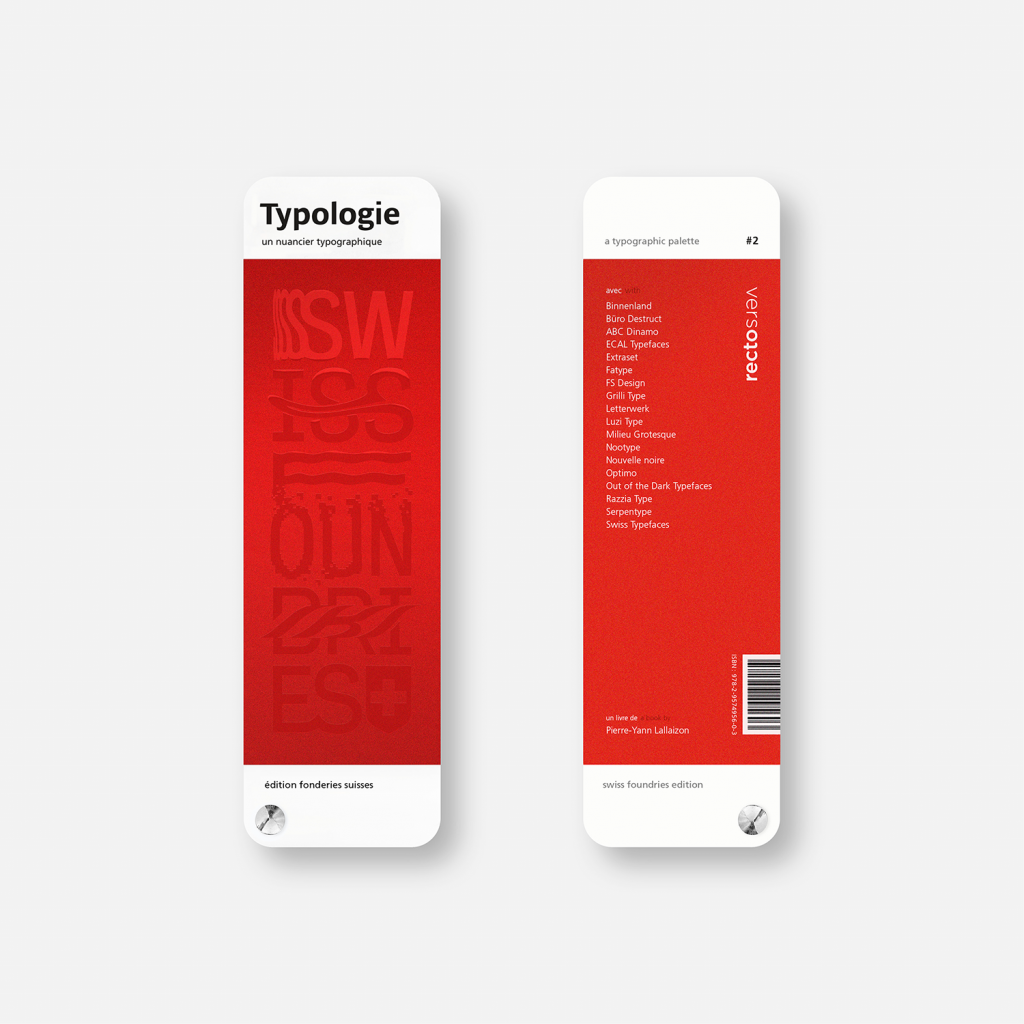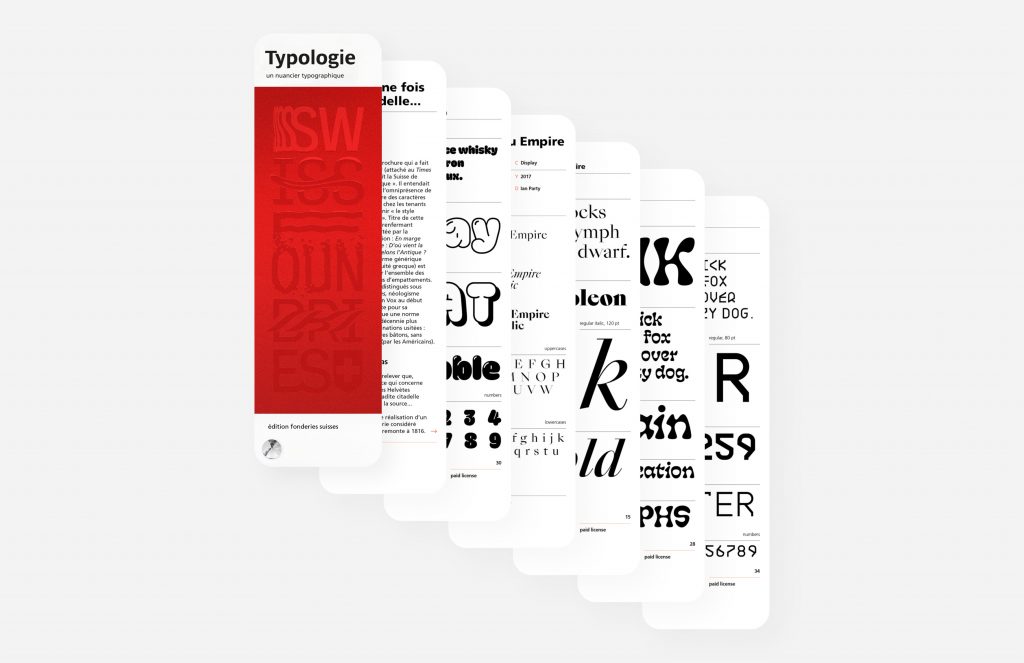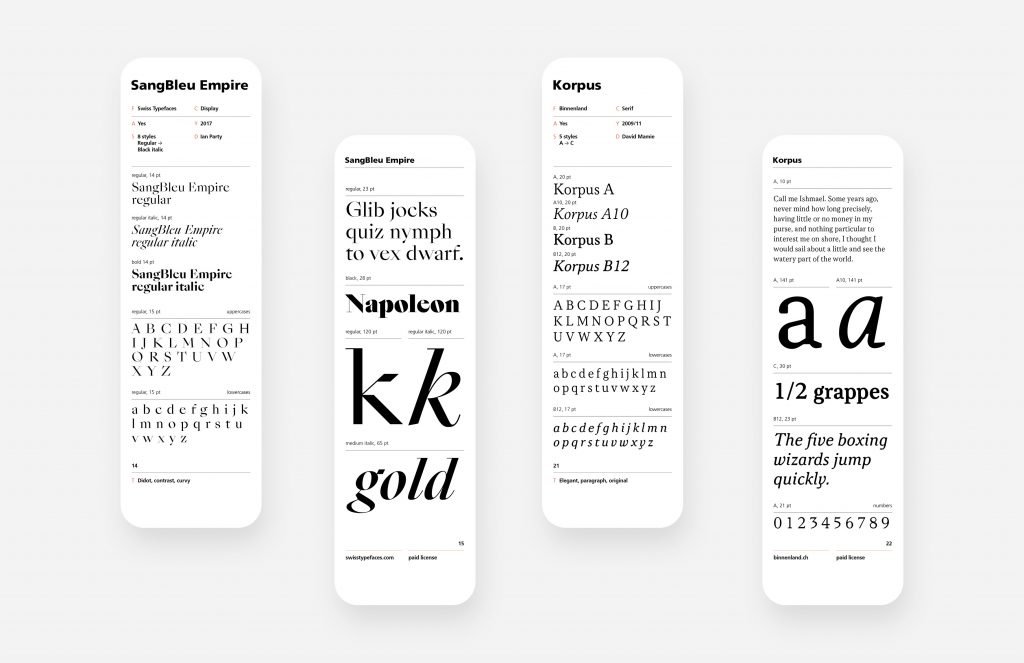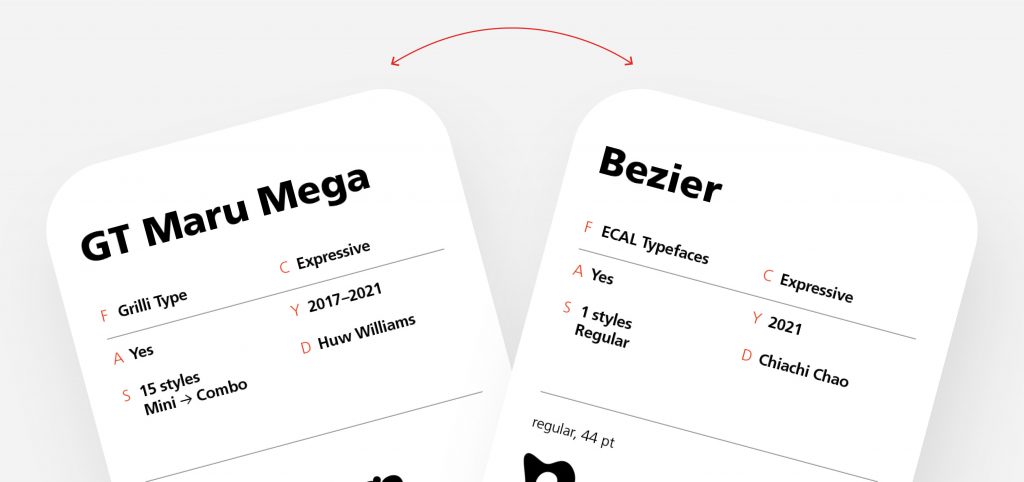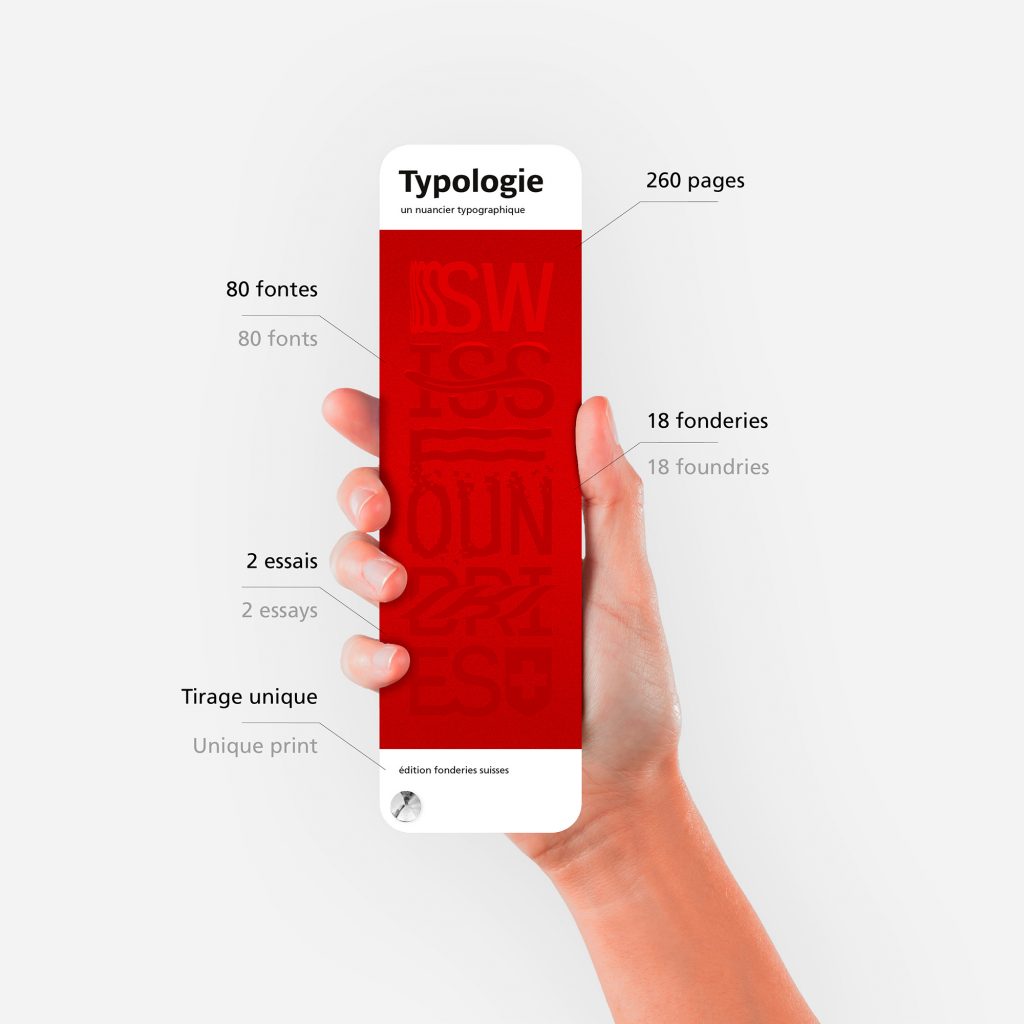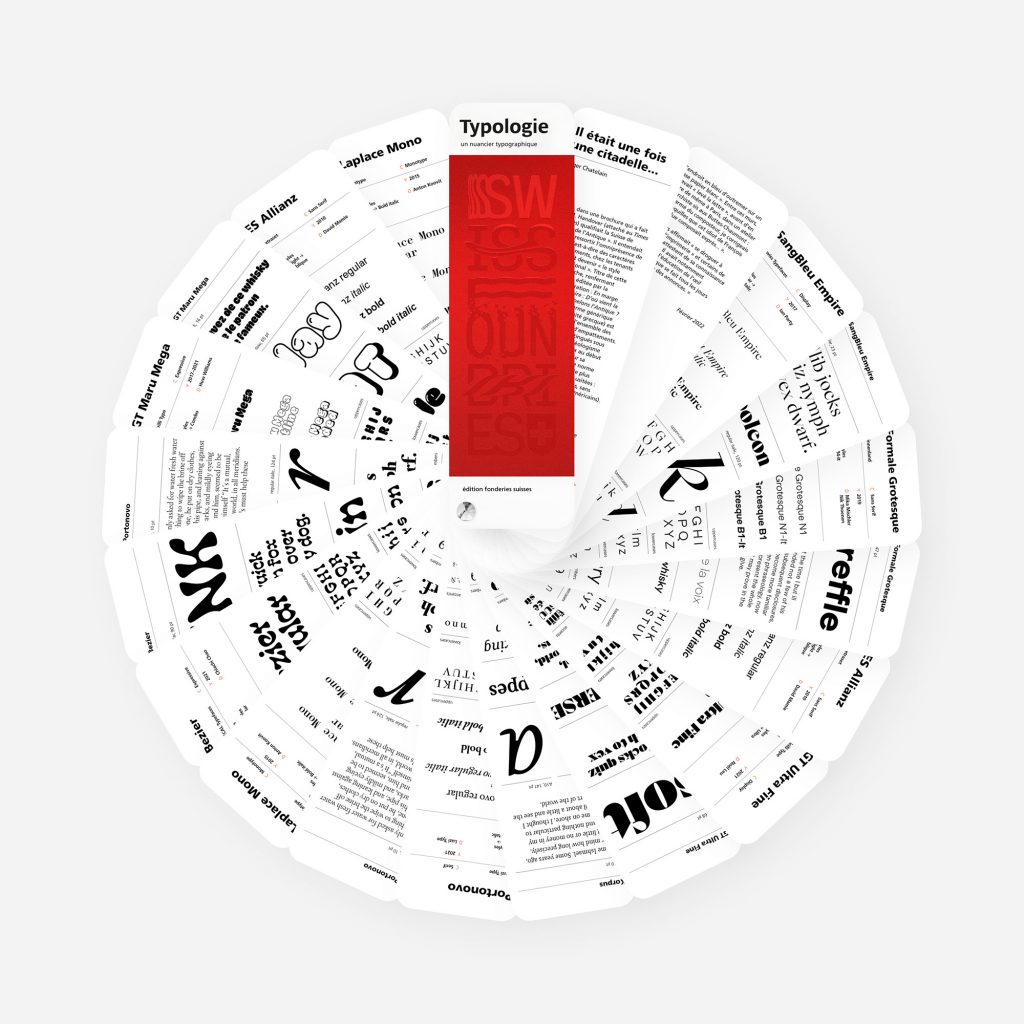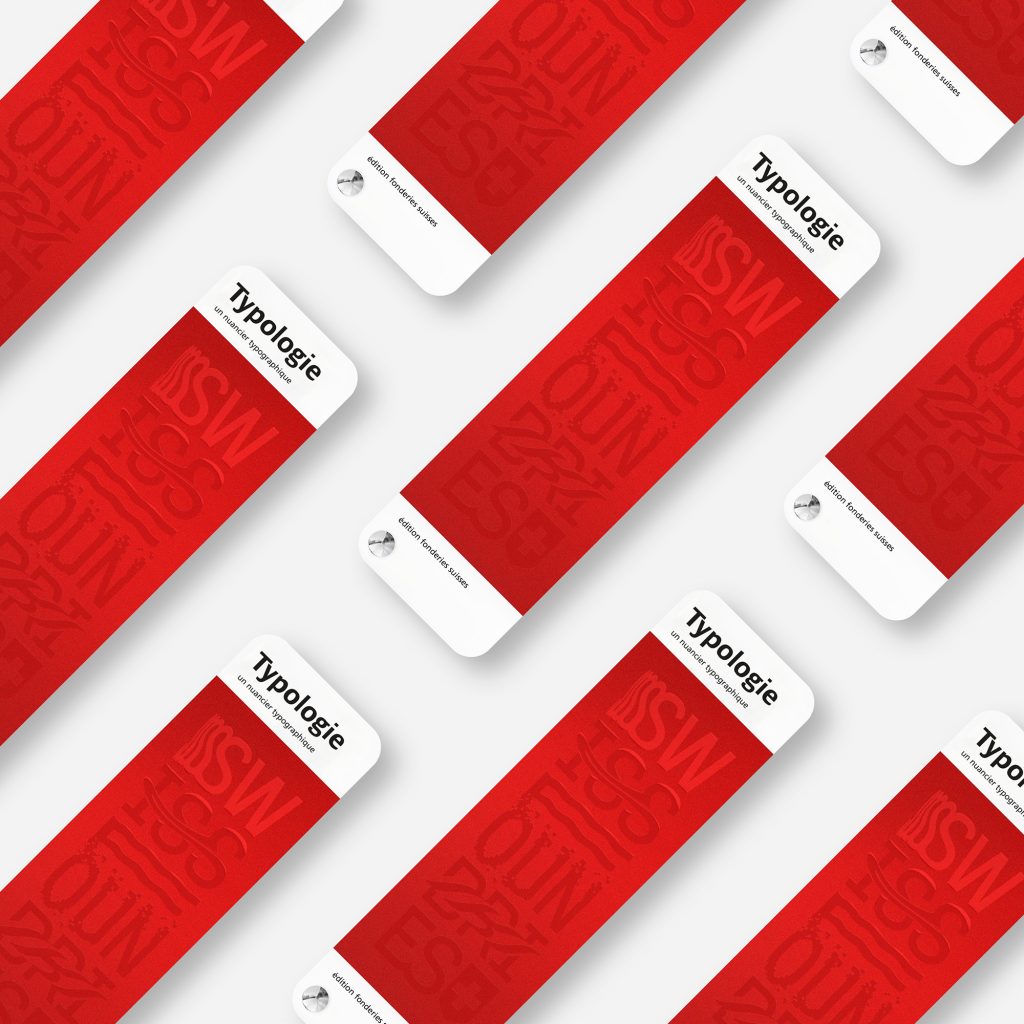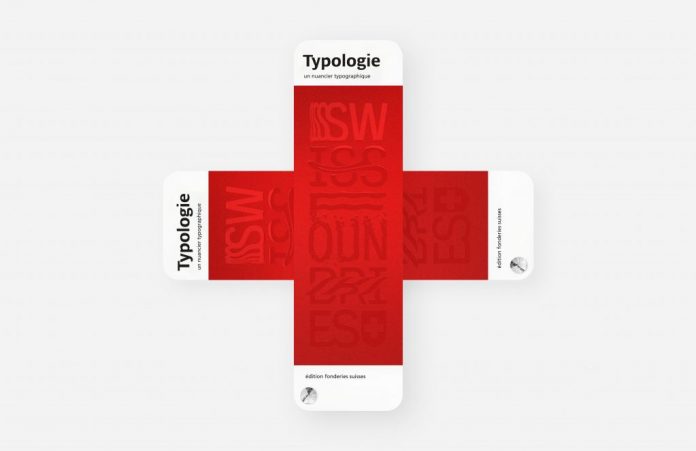
Typologie, nuancier de la typographie suisse en pré-commande !
Le studio de design graphique Recto Verso crée un nuancier typographique spécial fonderies suisses !
80 polices de caractères de dix-huit fonderies suisses sont présentées. L’on peut ainsi découvrir le SangBleu Empire, le GT Maru ou le Blender. Deux pages de spécimen sont dédiées à chaque caractère. Extraset, Swisss Typefaces, Grilli Type, Nootype, voici quelques-unes des fonderies représentées. Les polices sont classées en cinq grandes catégories : serif, sans serif, display, monospace et expressive.
L’ouvrage, mesurant 60 x 200 mm, est composé de 260 pages. Il est préfacé par le typographe Roger Chatelain et la couverture a été réalisée par l’artiste Rylsee. Ce nuancier, “Typologie”, est disponible en pré-commande sur Kickstarter. Il est un outil pour faciliter la combinaison de polices, un support créatif qu’il est possible d’apporter à un rendez-vous client, ou alors un catalogue d’inspiration — ouvrage de typographie à part entière !